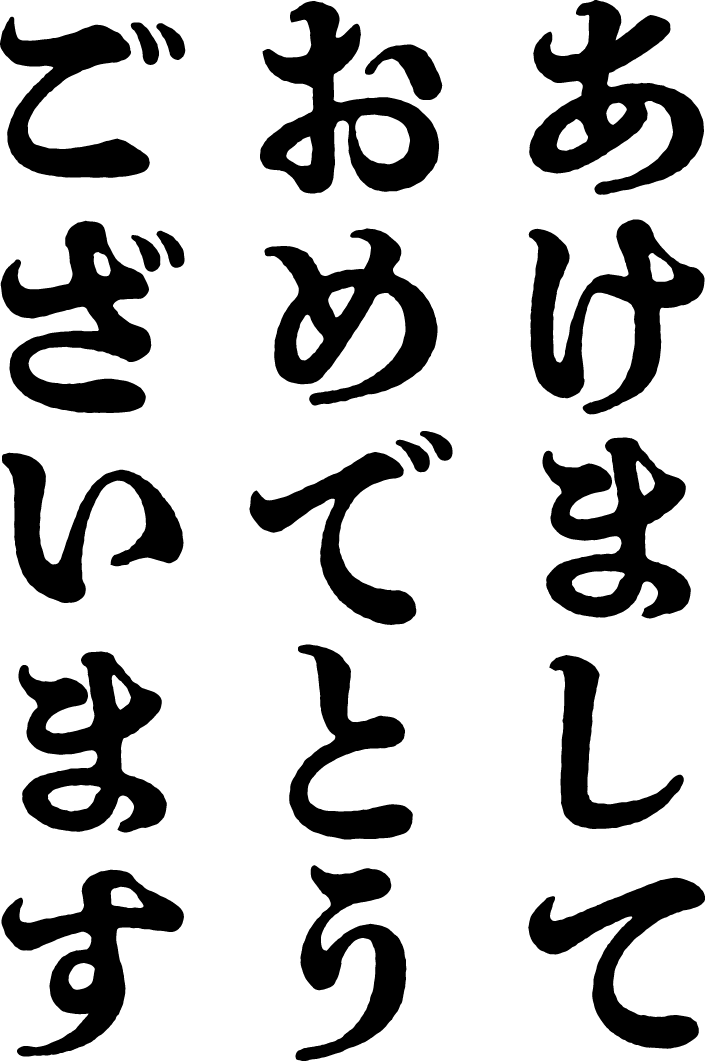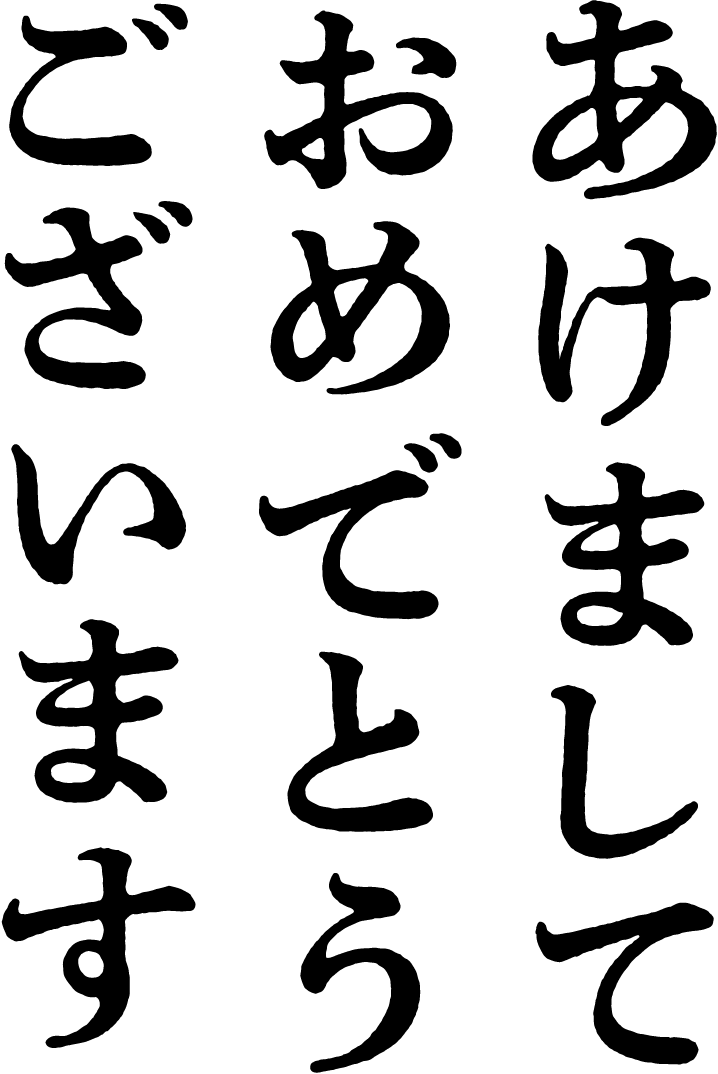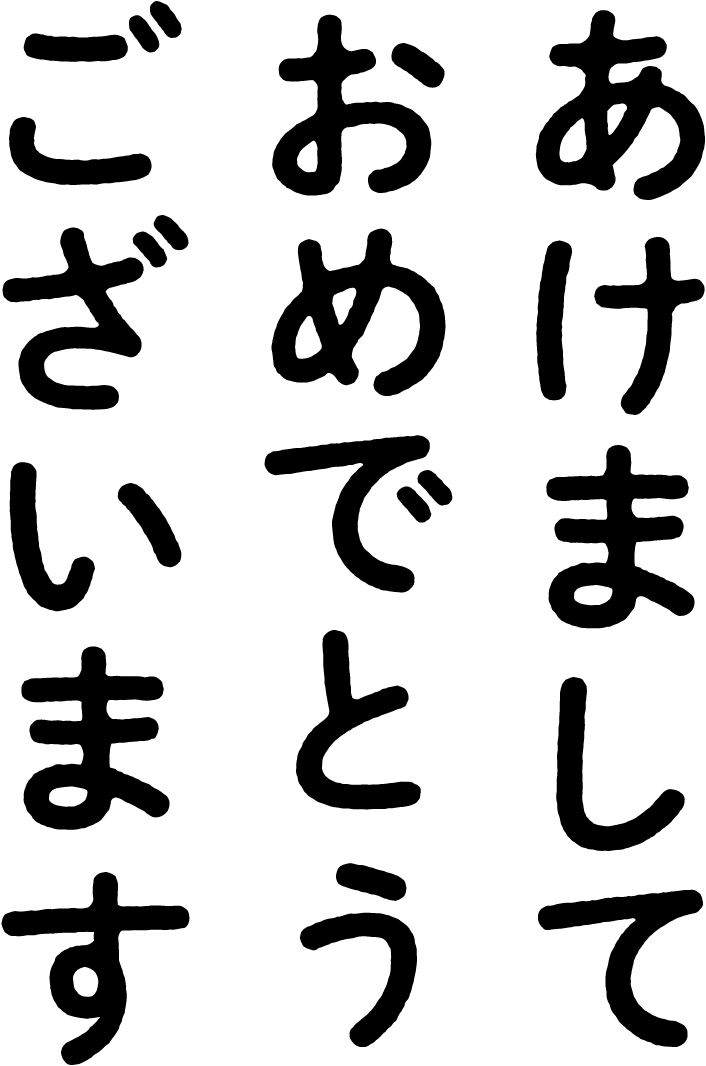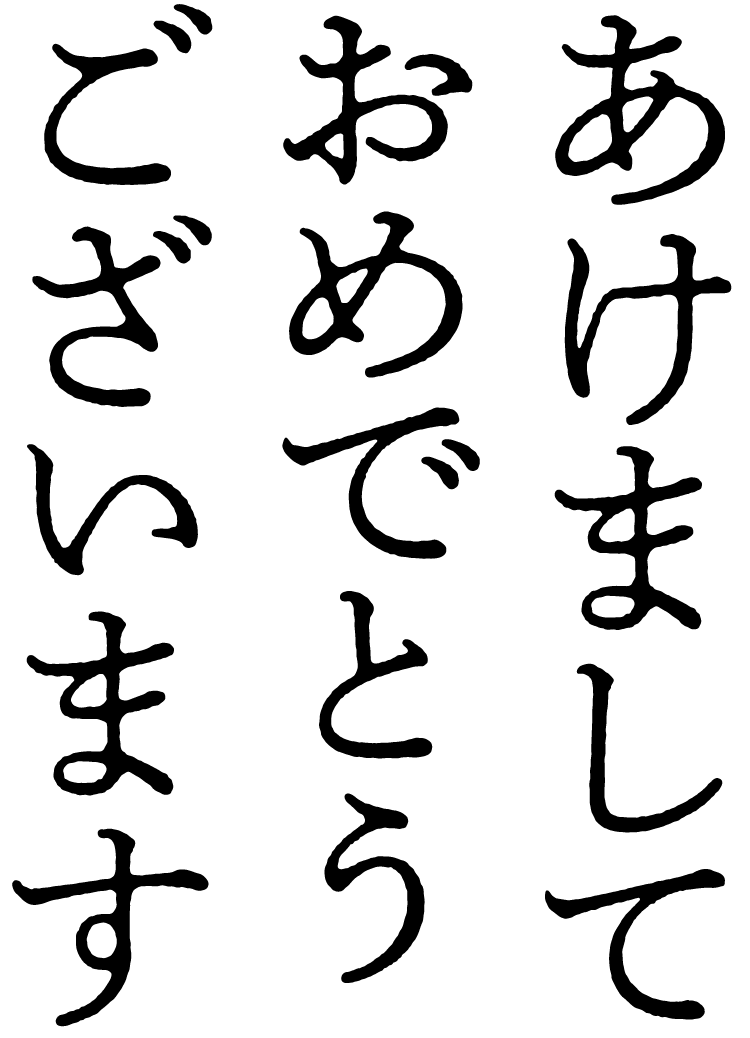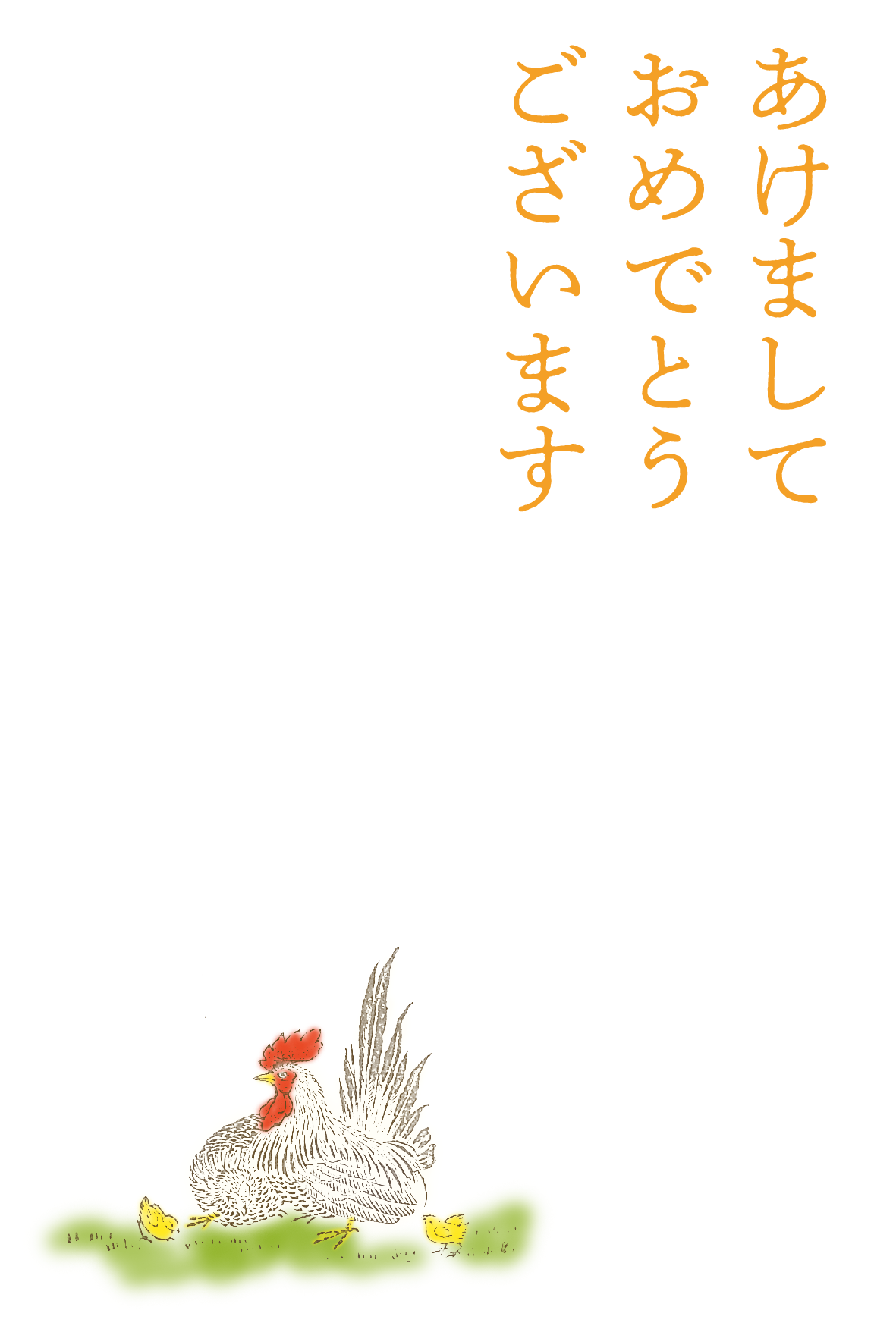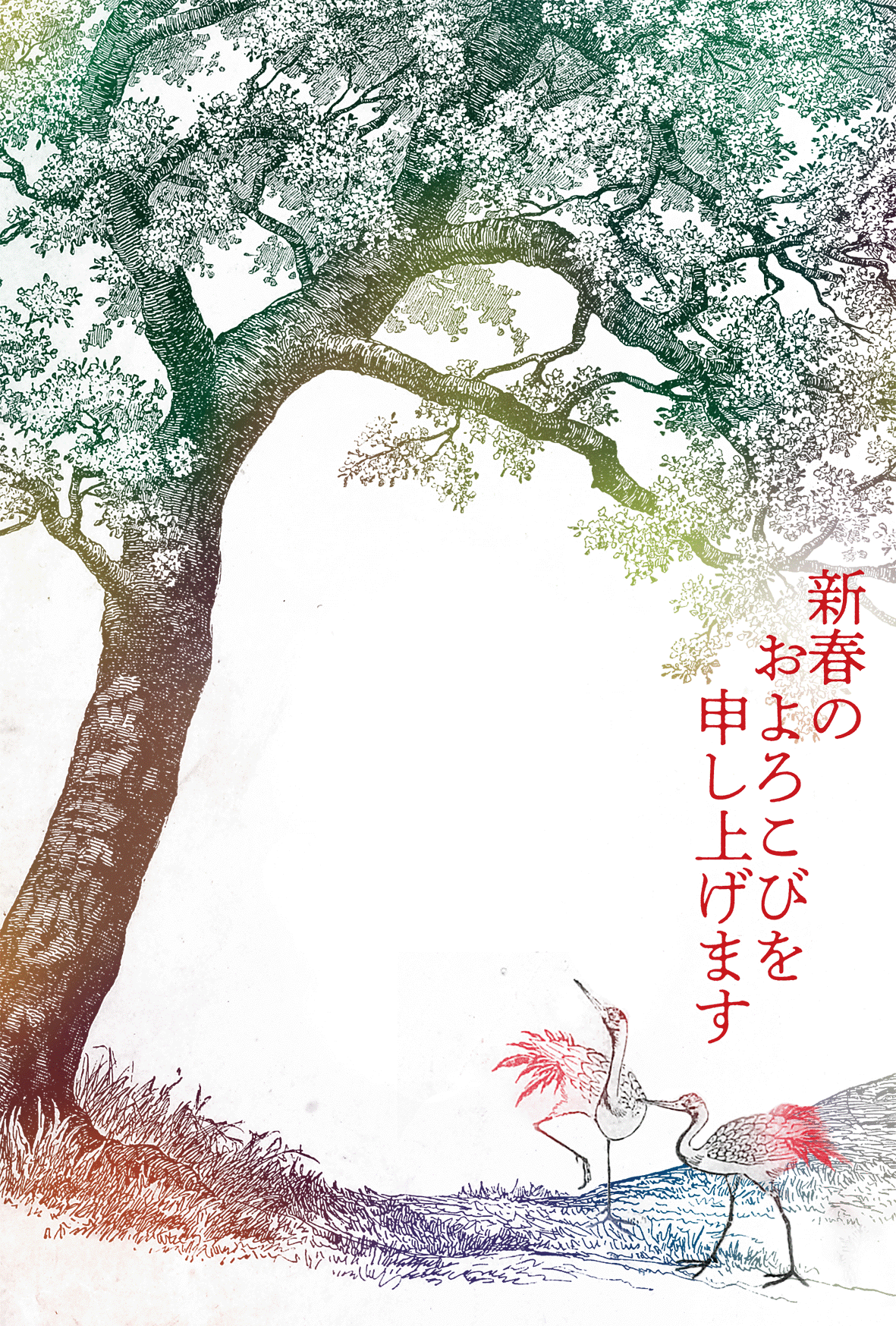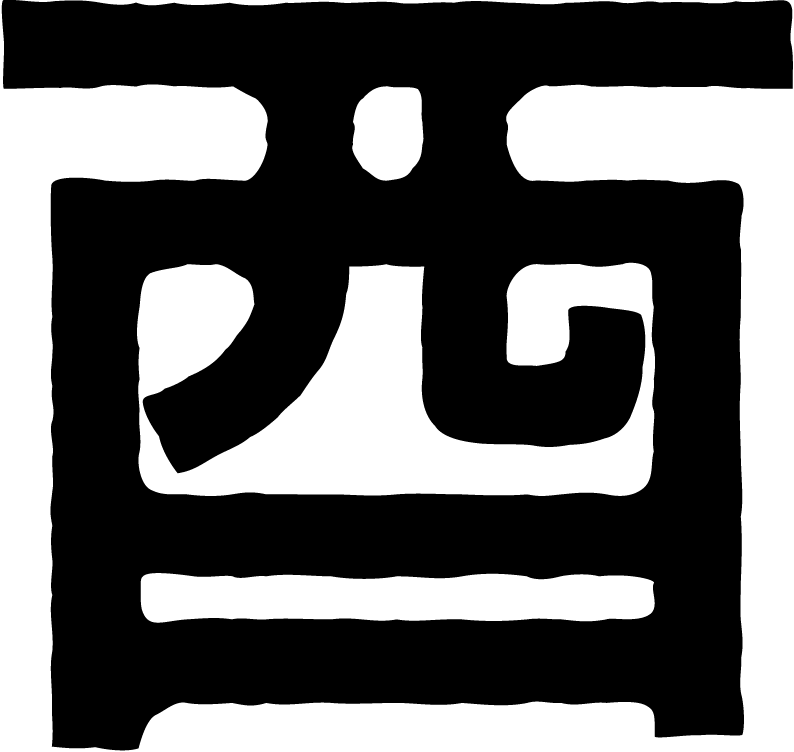
第39回 2016年は活字風な秀英体と『活版見本帖』で年賀状を作ろう!
今年も最後の月がやってきてしまいました。年々時間が経つのが早くなっているように感じます。
一年の感謝の気持ちと新たな年のご挨拶を込めた年賀状に秀英体はいかがですか?
今回のコネタでは、一年間のご愛顧に感謝いたしまして、恒例の「秀英体で年賀状」をお届けします。
新年のご挨拶には先月18日に提供を開始したばかりの新書体「秀英にじみ明朝L」を筆頭に、目下開発奮闘中のにじみシリーズ3書体を、イラストは秀英舎・大日本印刷が誇る最大規模の見本帳、大正3年版『活版見本帖 Type Specimens』から、来年の干支である「酉」をピックアップしてご用意しました。
定番のご挨拶
「あけましておめでとうございます」定番中の定番ですね!
縦組み、横組みをご用意しました。
書体によってにじみ方も変わってきます。お好きな雰囲気のものをお選びください。
左から
賀詞
賀詞の定番、「迎春」「謹賀新年」もご用意しました!
「秀英アンチック」「秀英四号太かな」はかな書体のため、こちらの賀詞は、それぞれ、おすすめの組み合わせ「秀英角ゴシック金 B」「秀英初号明朝」のにじみフォントを用いています。
2017年の干支は「酉」です!
来年の干支は「酉」ですので、この一文字をバーンと大きく使いたいですね。
個性さまざまな秀英体を試して、お気に入りの「酉」を見つけてください。
挿絵にはインパクトのある鳥のイラストをどうぞ!!
秀英体見本帖から、秀英体のLINEスタンプでおなじみの鳥を含め、個性豊かな鳥のイラストをご用意しました!
そのまま出せちゃう!?
使ってみたいけど、組み合わせるのがちょっと面倒だなぁ…という方向けに、テンプレートもご用意しました!
こちらのテンプレートを年賀はがきに印刷して、あとはひと言お気持ちを添え書きするだけ!!
年末は時間がない! という方にもオススメです。
今年はかな書体や角ゴシック金銀Mに続き、「秀英にじみ明朝L」などさまざまな新書体をリリースすることができました。
開発中のにじみシリーズも、皆さまのお手元で使っていただける日が楽しみです。